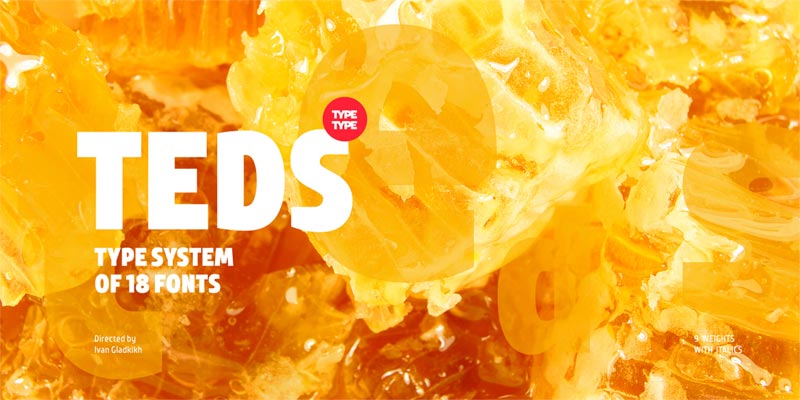
Font Teds
Do naszego studia trafił nowy font Teds. Został zaprojektowany w 2016 roku przez Ivana Gladkikh z Rosji. Font posiada polskie ogonki oraz 9 odmian grubości. Teds to skondensowany i nowoczesny font.